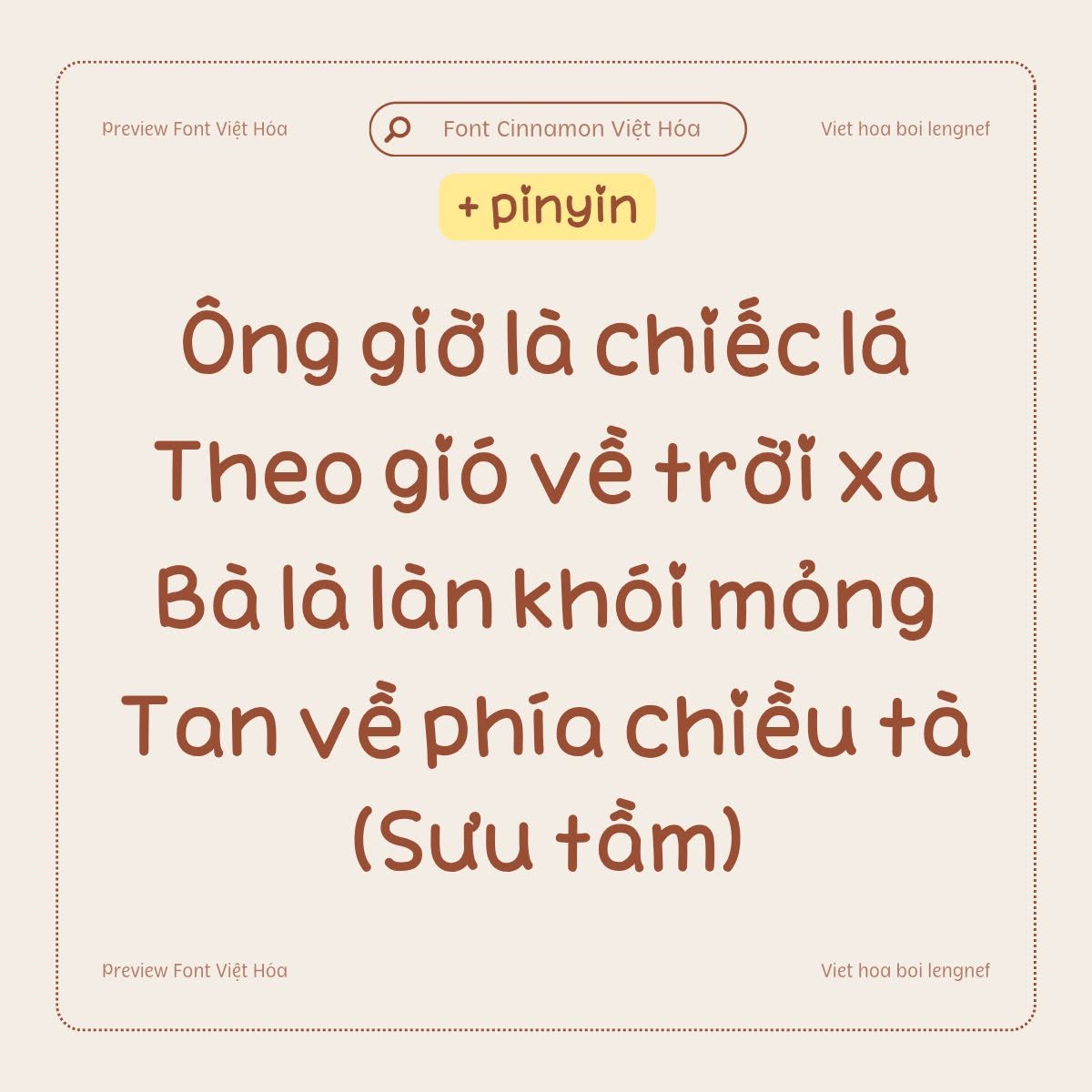
Việt hóa theo yêu cầu 22 || LF Cinnamon
- Tác giả: soffr_nv
- Việt hóa: lengnef
Cinnamon là kiểu font viết tay to tròn, dễ thương được tác giả chia sẻ trên Thread. Phù hợp với các dự án cute.